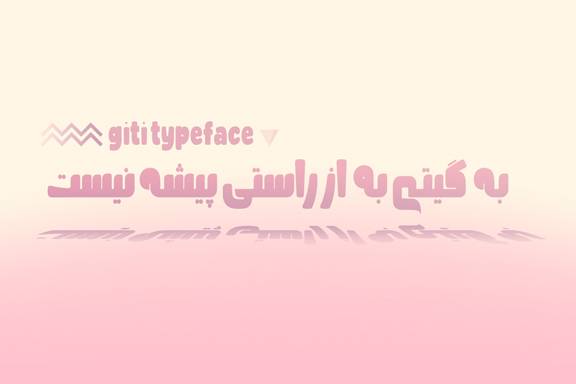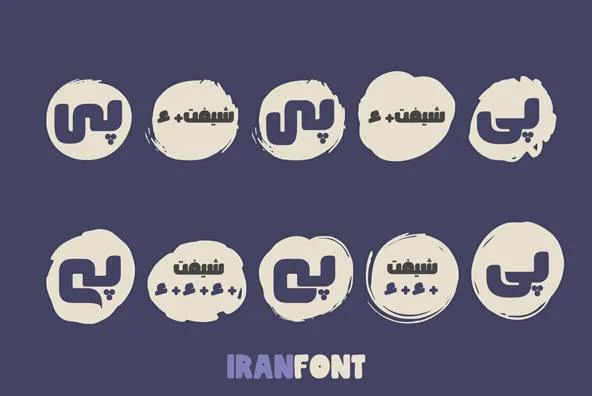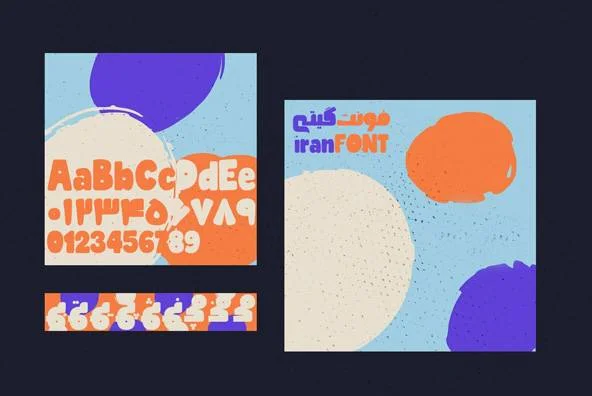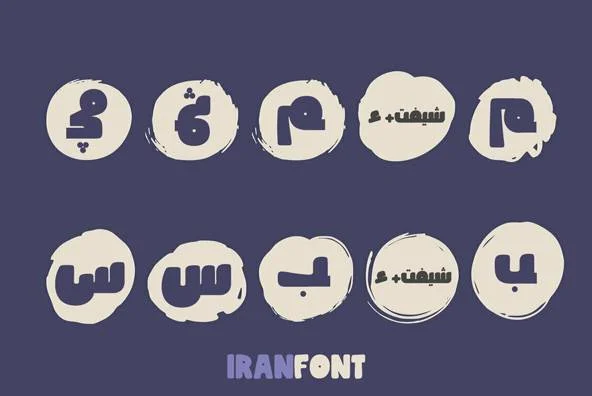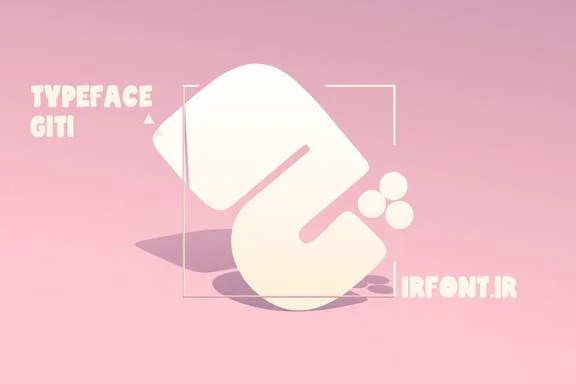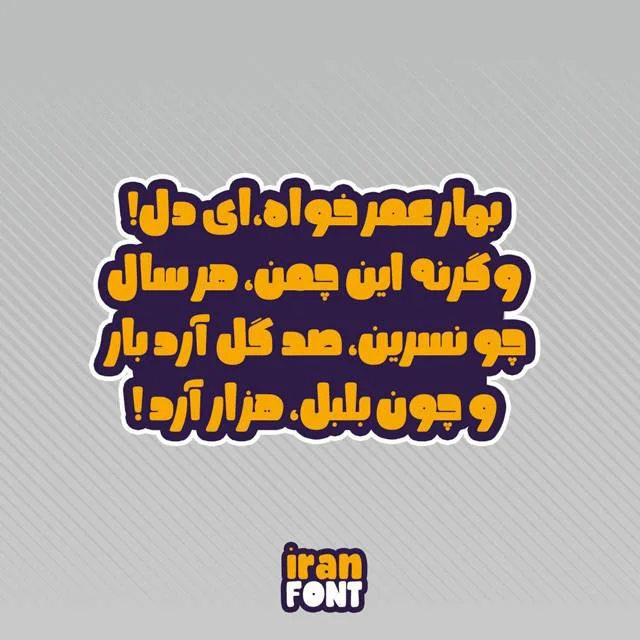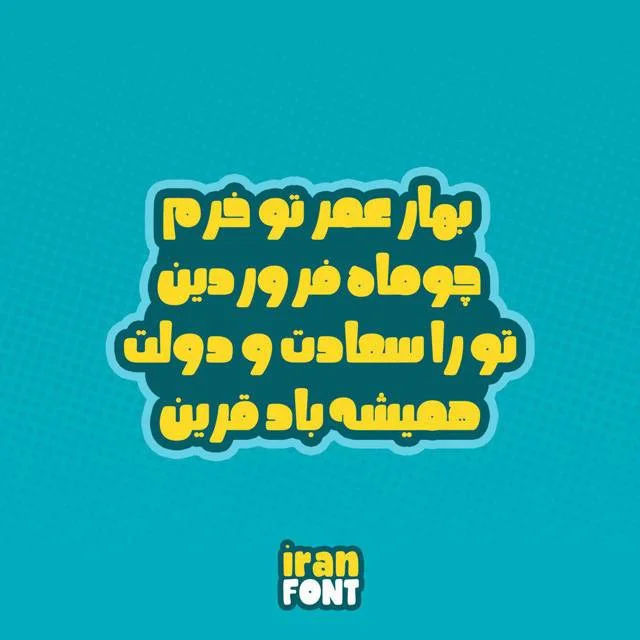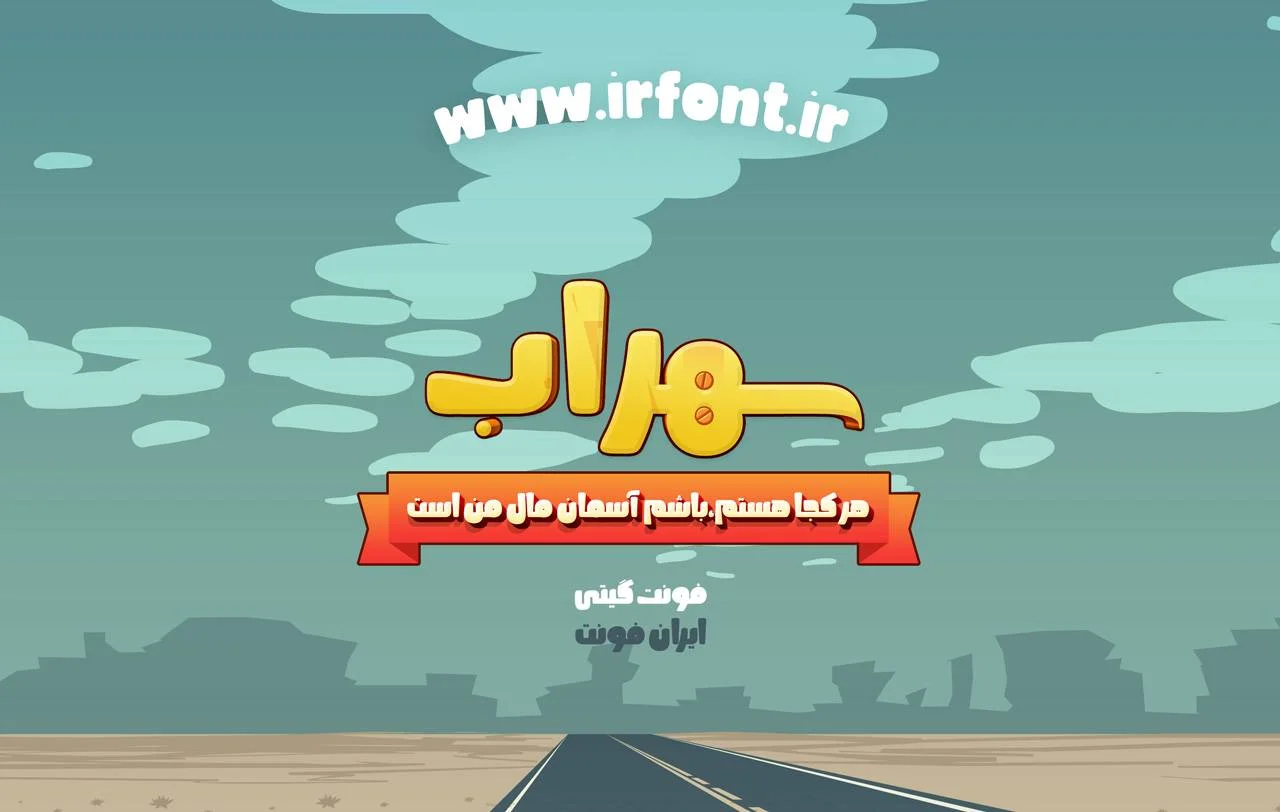
فونت گیتی
فونت نمایشی گیتی
ریحانه غلامی
فونت فارسی گیتی
فونت گیتی فونتی با کاربرد نمایشی است طراحی ابتدایی این فونت با استفاده از ماژیک و به صورت آزادانه ،بدون در نظر گرفتن اصول طراحی و به صورت بداهه انجام شد و سپس با ویرایش ها و اصلاحات متعدد و اضافه کردن حروف ترکیبی و جایگزین سعی شد حروف به صورت کاربردی طراحی شوند و در اختیار کاربران قرار بگیرد. در ادامه طراحی ابتدایی فونت گیتی را ببینیم.
فونت گیتی | giti-typeface
فونت گیتی بر پایه‌ی استفاده از ماژیک و به صورت آزادانه سال 1396 توسط ریحانه غلامی آغاز و در فروردین ماه سال یک هزار و سیصد و نود و هشت جهت استفاده به پایان رسیده است ، ساخت این تایپ فیس در ایران فونت به کوشش مسلم میان آبی به اجرای نرم افزاری رسید
چند نمونه طراحی کاور از فونت گیتی ببینیم
و ارسالی یک کاور زیبا از یکی از همراهان همیشگی ایران فونت
در فونت گیتی امکان استفاده از شکل حروف و ترکیبات چندگانه جایگزین (alternative) وجود دارد. مثلاً در تصویر پایین می‌بینید که کلمه شهرزاد به چند شکل مختلف تایپ شده است. (راهنمای چگونگی استفاده از ترکیبات جایگزین در بسته دانلودی موجود است ، حال برخی از ترکیبلات رو باهم ببینیم ) فونت گیتی دارای 6 حالت حرف (ی) و ترکیبات حروف (م) است.